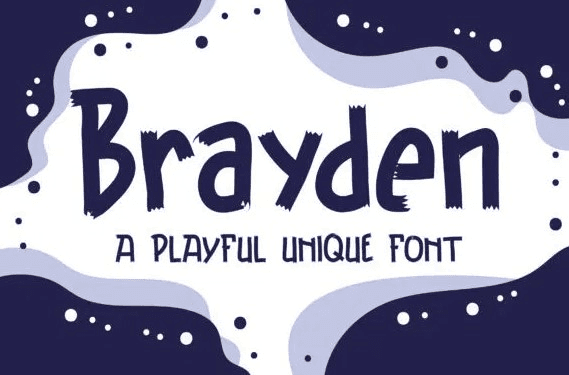
Brayden Font
Brayden - это веселый и игривый шрифт дисплея. Он воплощает в себе радость и подлинность и является идеальным выбором для любой детской деятельности или школьного проекта.